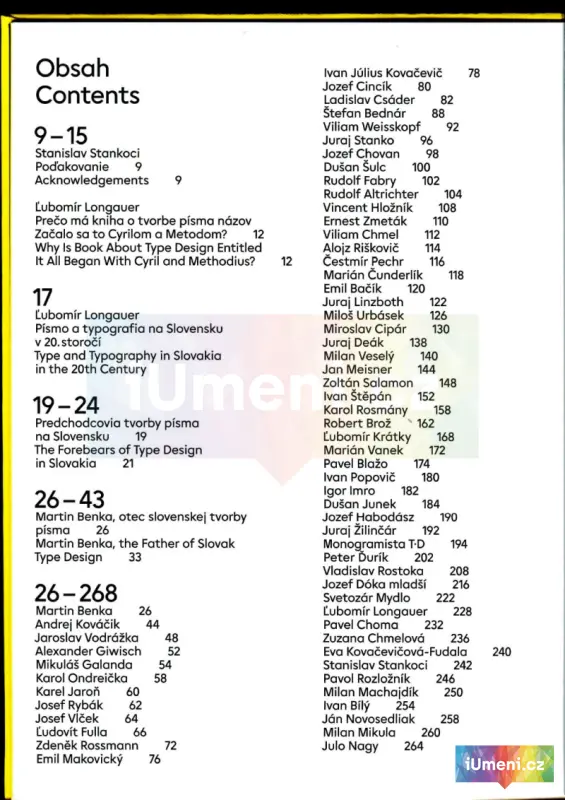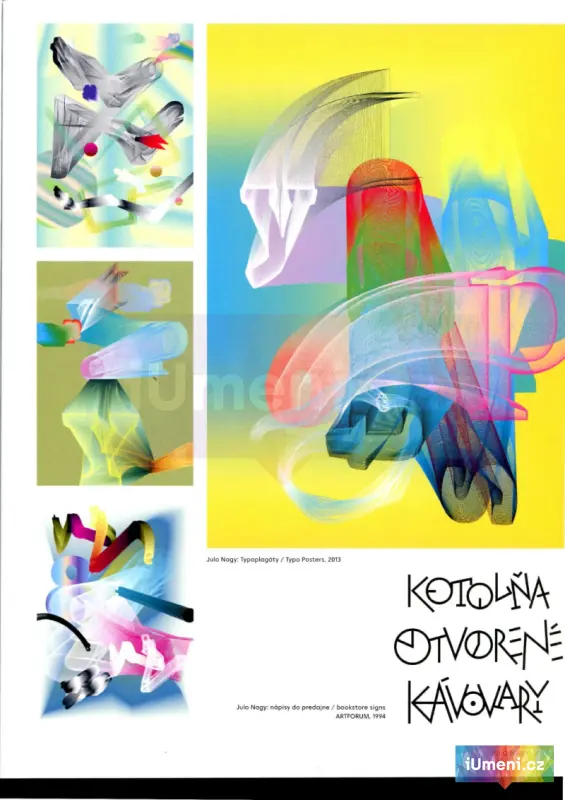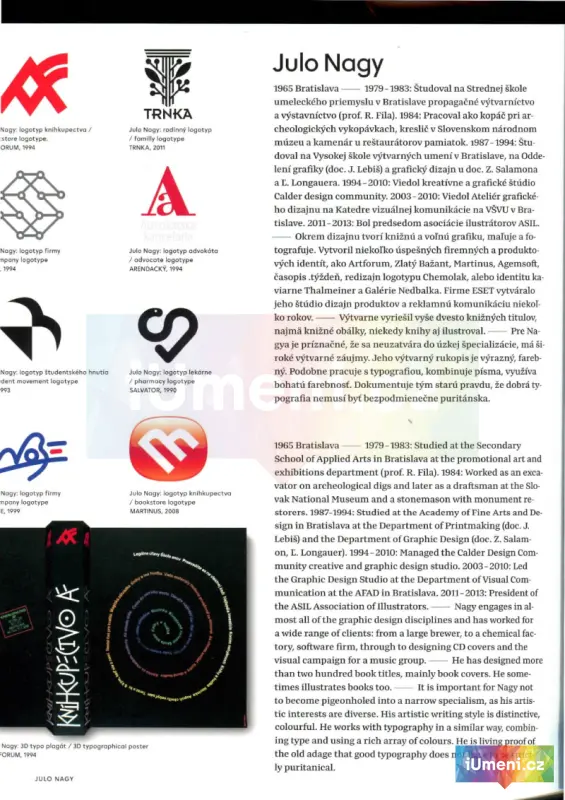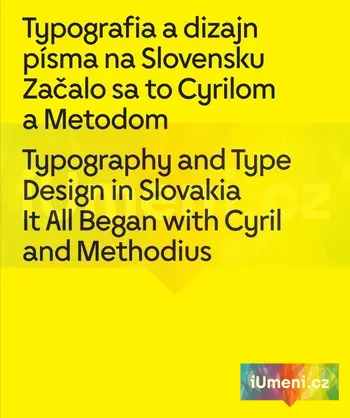
Typografia a dizajn písma na Slovensku. Začalo sa to Cyrilom a Metodom
"Publikácia, ktorú držíte v rukách, sprevádza nielen rovnomennú výstavu, ale jej poslaním je aj dokumentovať vývoj grafického dizajnu a výsledky práce grafických dizajnérov v oblasti typografie a tvorby písma na Slovensku.
Aj keď história písma je príbeh starý šesťtisíc rokov, tohtoročné pripomenutie si 1150.výročia príchodu sv. Cyrila a Metoda na Veľkú Moravu a ich prínosu pre našu kultúru bolo pre nás impulzom k zrodu myšlienky zaznamenať a prezentovať najkvalitnejšie výstupy tvorby slovenských grafických dizajnérov a typografov spôsobom a rozsahom, aké doteraz ešte neboli realizované, vrátane tejto publikácie. Naším zámerom bolo poskytnúť verejnosti výnimočnú príležitosť spoznať oblasť, ktorá je, bohužiaľ, na okraji kultúrneho záujmu a je len veľmi sporadicky prezentovaná. No predovšetkým sprostredkovať bohatstvo našej tradície v tvorbe písma a jeho využívania a spoločensko-kultúrny záväzok tútotradíciu chrániť, ďalej ju rozvíjať a vytvárať dobré podmienky na podporu súčasnej tvorby písma a typografie. V rámci ich prezentovanej tvorby má verejnosť možnosť spoznať písmo z iného pohľadu, než na aký je zväčša zvyknutá - vnímať ho ako kultúrny fenomén, v jeho formálnej aj funkčnej rozmanitosti, môže sledovať historické štýlové premeny typografie či tvorivý prínos jednotlivých autorov k rozvoju tejto oblasti vizuálnej komunikácie. V tomto projekte sa spojili dve koncepcie bádania a dokumentovania tvorby písma a typografie na Slovensku, od začiatku 20. storočia až po súčasnosť. Historická časť je výsledkom niekoľkoročného systematického výskumu Ľubomíra Longauera, zatiaľ čo prehľad tvorby za posledných dvadsať rokov spracoval Palo Bálik. Obidve časti odkrývajú prekvapujúce veci, javy a súvislosti sprevádzajúce vývoj v danej oblasti a verejnosti ponúkajú kvalifikovaný prehľad, analýzu a stručný popis tvorivých počinov v problematike písmarstva a typografie. Každá z nich je nielen cennou informáciou o autoroch a stave a kvalite tvorby v tomto médiu, či jeho poznania, ale je po mnohých stránkach inšpirujúca pre súčasnosť, ponúka širokú škálu úvah a možností pre budúcnosť."
- Stanislav Stankoci, rektor VŠVU v Bratislave
„Perfektní kniha o vývoji grafického designu a typografii na Slovensku. Více takových.“